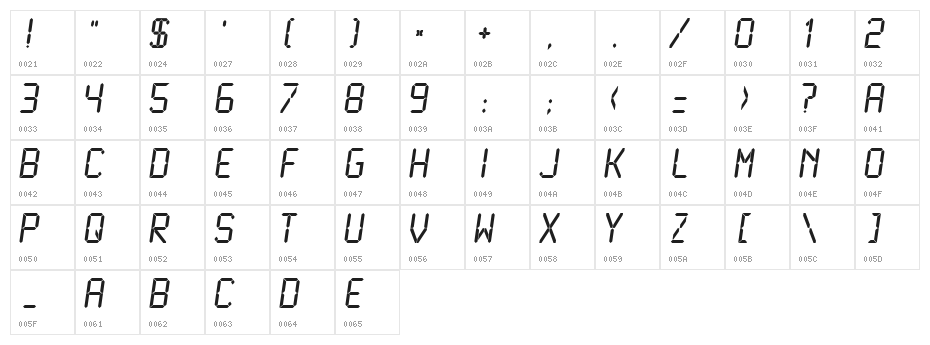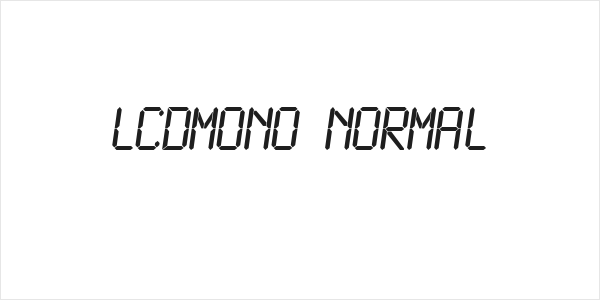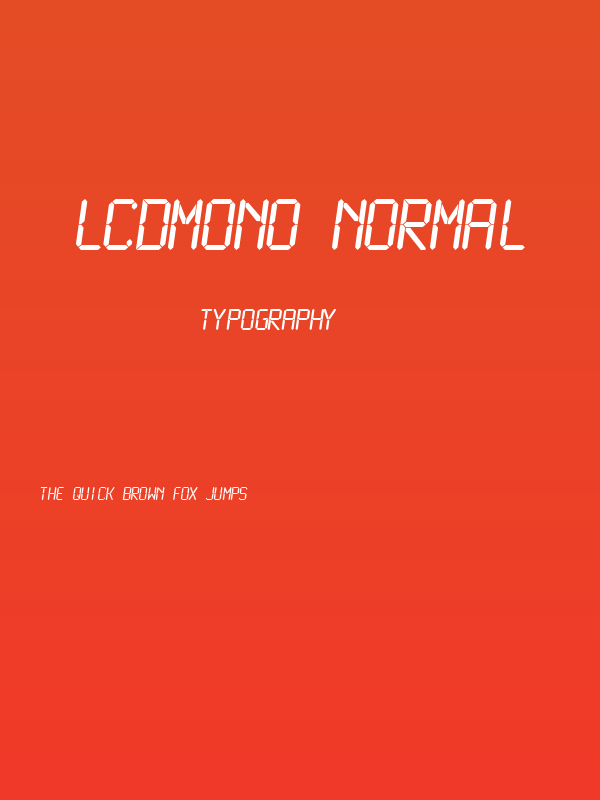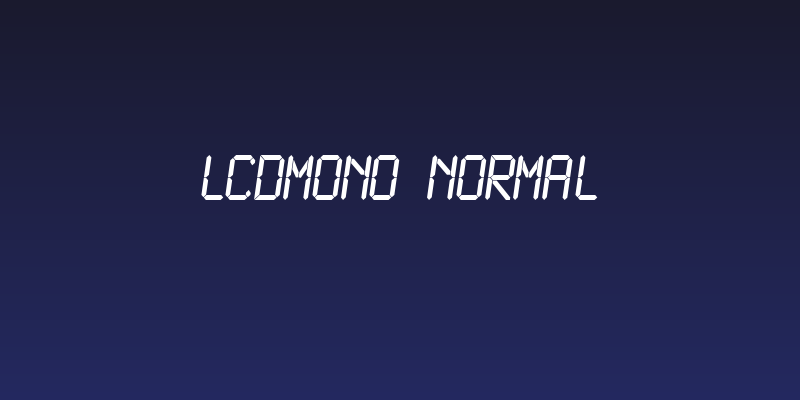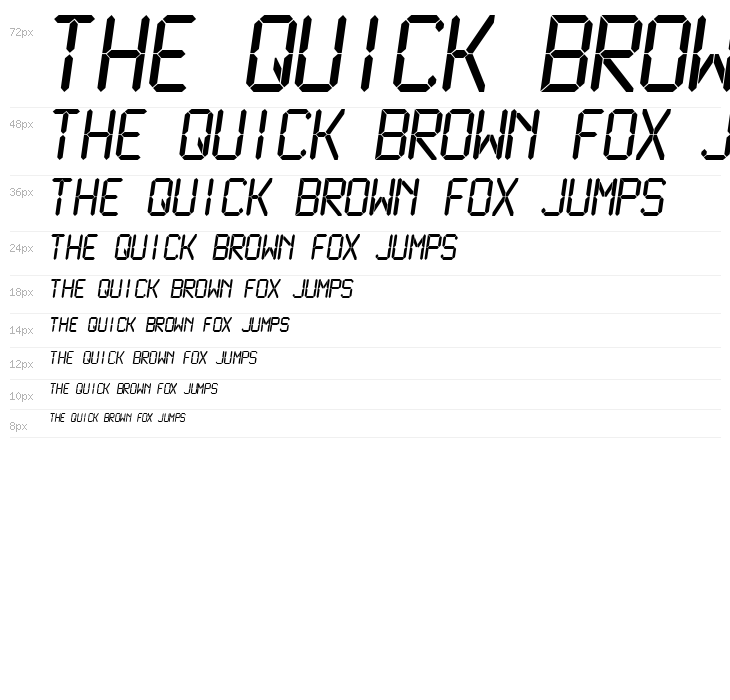
LCDMono Normal Font
| उपयोग का मामला | Headlines, Digital displays, Tech interfaces |
| सुझाए गए प्रोजेक्ट | Ideal for digital interfaces, tech-themed designs, electronic device displays, and retro-futuristic projects. |